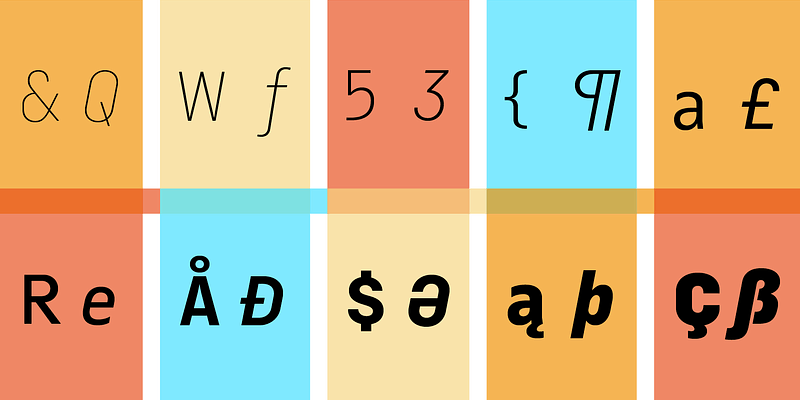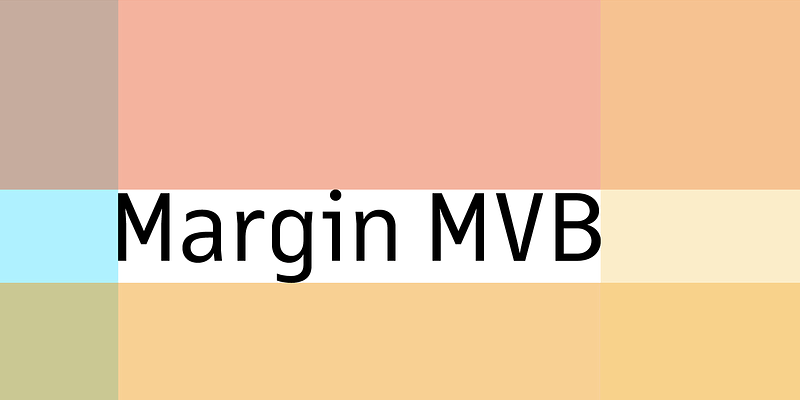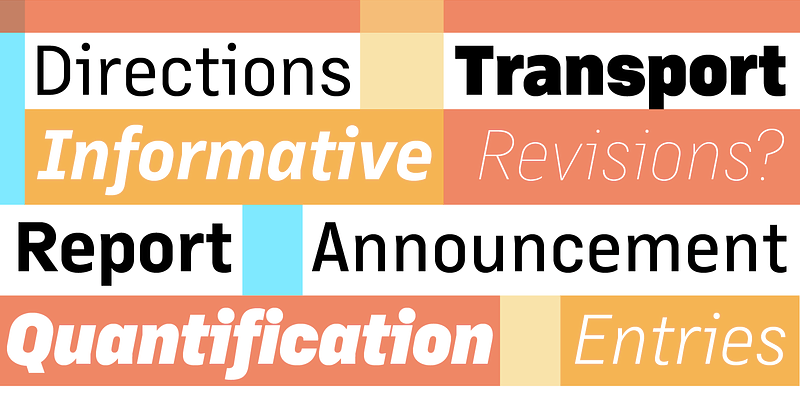
MVB Margin был вдохновлен моноширинным шрифтом, состоящим только из заглавных букв, который когда-то широко использовался в банковских выписках и счетах за коммунальные услуги. В основу этого нейтрального, утилитарного семейства Марк ван Бронкхорст заложил современный пропорциональный шрифт со строчными буквами, наборами цифр и маленькими заглавными буквами. Гарнитура включает множество начертаний: курсив и несколько видов толщины. Четкий технический шрифт MVB Margin отлично подходит для печатного текста, экранов и хорошо смотрится в небольших размерах.